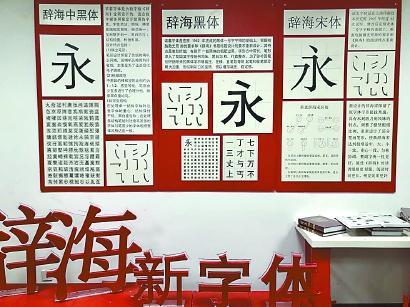
第四代传承人为《辞海》(第七版)设计的新字体。 资料图片
用手机发微信、翻开书本阅读……当一个个汉字如同空气一般出现在你眼前时,你可曾想过,这些字体是由谁设计出来的?
新闸路1209弄60号印研工坊内,“现代汉字印刷字体发源地”和“上海印刷字体展示馆”两块招牌今天同时揭牌。人们最常用的宋体、黑体、仿宋、楷体这四大经典印刷字体,正是在这里诞生的。
弄堂口的门牌已改造一新,显示“印研工坊”始于1956年。新中国成立后在上海建立的专业印刷科研机构——上海市印刷工业公司试验室驻扎在这里,1961年8月改为上海印刷研究所,1965年更名为上海印刷技术研究所。去年,上海印刷集团和上海印刷技术研究所在“印研工坊”园区改建完成,搬回新闸路1209弄60号。
新改建后的“印研工坊”园区处处可见对印刷文化、字体文化的展示。面向市民开放的“上海印刷字体展示馆”分“字体馆”与“非遗馆”,在此可一览汉字印刷体的源流与发展。
现代汉字印刷字体两个“源头”
何以能称“现代汉字印刷字体发源地”?新闸路的这处小楼里,找得到两个“源头”。
其一是新中国的印刷字体源头。在相当长一段时期,我国汉字字体、字形杂乱,异体、变体混合使用,严重影响印刷质量和阅读效果,更导致我国参加国际书籍装帧博览评比无功而返。1959年,文化部召开会议指导上海率先进行“印刷字体改革”,以印研所为基地,集聚了沪上美术创意有功力、书写正楷有造诣、雕刻字模有经验的三股人才,成立50多人组成的字体研究室。于是,字体设计师这一职业,从1960年开始在中国创立。
印研所字体研究室的设计人员耗时5年,相继完成宋、黑、楷、仿四种常用印刷字体的创写设计,总计8万字,分别用于印刷新版横排本《毛泽东选集》《辞海》《汉语大字典》及政经科教图书、期刊杂志和中小学课本,我国出版物和印刷品面貌就此焕然一新。在创作的同时,设计人员还根据标准化、规范化的笔形、字形编制出《印刷通用汉字字形表》,报经国家文字改革委员会审核通过,成为我国印刷汉字模板,为新中国推广简化字和汉字使用的规范化作出重要贡献。
其二是汉字印刷字体的数字化发展始于此。上世纪80年代,上海印刷技术研究所将宋、黑、楷、仿四大品种的专用字稿作为与英国蒙诺公司合资的投资,首次购进国际先进的激光照排设备,后又将这四种字体的原始字稿复印无偿提供国家“748”工程、“汉字信息处理”重大项目。这些字体与现代数字信息技术结合,成为发明“汉字信息处理激光照相排字技术”的原创母体,之后普遍进入海内外汉字字库,派生出千姿百态的后代字体。
2009年,上海印刷技术研究所申报的汉字印刷字体书写技艺被列入上海市第二批非物质文化遗产项目名录。
五道工序反复雕琢出完美字体
在印研所标志性的旋转扶梯,1964年夏日,6个穿衬衫的小伙站在三到四楼的拐角拍照,最前面的陈其瑞21岁,年纪最小,身后张家声、过祖良、陈永海、许柏康、徐学成等拾级而上。如今,旋转扶梯的墙面成为非遗传承人墙,23位非遗传承人的照片拾级而上。排在陈其瑞之前的11位“第一代”传人皆已谢世。
1943年出生的陈其瑞18岁进入印研所,跟着当时所里的前辈们参与“黑一体”创写,上世纪70年代与张家声共同主持“新魏体”开发,至今被广泛使用。“当时,平均一个人每天能写四个字。”陈其瑞介绍。
设计字体要经过五道工艺流程。首先是铅稿,设计者用铅笔在专用字稿纸上勾勒出字稿轮廓,这是字体成败的关键;第二步是画线,用画线工具直线笔(鸭嘴笔)画出黑色线条,要求墨色均匀一致,线条光洁;第三步是勾描,用描笔将设计好的字形轮廓勾描出来;第四步是填黑,将黑墨色填满勾描内的留白部分;最后一步是描白,严格依照字样规范、笔形进行修整、精加工,用白色颜料涂去毛刺、毛边,使线条、笔形光洁优美。在“非遗馆”展示的当年字体设计原稿上,铅笔勾勒与描白依然可见,有的字还有贴补痕迹,可见当年设计师们经过反复雕琢才有了日后应用的完美字体。
1957年出生的汉字印刷字体书写技艺第三代传承人原伟民介绍,40多年前诞生的“宋一体”“黑一体”是新中国第一款专为《辞海》正文和配套标题用字所设计的字体;“宋二体”“黑二体”是专为《毛泽东选集》横排本正文及配套标题设计的首款字体;“仿宋体”主要为党政机关文件正文排版设计;“正楷体”主要为排印小学教科书和少儿读物设计。“常用经典字体的母体,就在上海,就在印研所。希望展示馆的开放能让更多人了解现代汉字印刷字体的起源和发展,了解汉字印刷字体的设计规范和创写工艺,更加热爱汉字。”原伟民说。
上世纪70年代,“书法体”首度引入印刷字体,首先选中的就是当时很受百姓喜欢、适合做店招和刷标语的“新魏体”,并确定找书法家来写字模。为了找到合适的书写者,陈其瑞骑着自行车走街串巷,看路两旁的店招。直到今天,陈其瑞仍然喜欢看店招。尽管很少有人知道字体背后的设计者,但他觉得,在那些字体里可以感受到当年辛勤工作的意义。
设计《辞海》(第七版)专用字体
去年在网上,出现一份叫价1万元的上海印刷技术研究所文书档案,其中包含第一代字体设计师的集体签名。这份上世纪60年代的文件背后是关于“宋七体”的一段往事。当时印研所已完成“宋一”“黑一体”“宋二”“黑二体”及“宋三体”,新设计的字体按序应编“宋四”,因沪语谐音不好听而改名“宋七”,即去年离世的汉字印刷字体书写技艺第一代传承人徐学成设计的“康熙字典体”。2010年,90后设计师厉向晨完成含47037个字的“康熙字典体”,在后来的“汉字热”中,成为传统、古典设计风格的代名词,“宋七”也随之重新进入人们的视野。“最美的宋体是哪一款?”有字体爱好者回答,“宋七”。
在新开放的上海印刷字体展示馆里,市民就能发现神秘“宋七体”的故事。最令人惊喜的或许是印研所今年创写的三种新字体的样张——“徽逸体”“逸文体”“新行楷体”。它们的设计者是印研所的年轻人,汉字印刷字体书写技艺的第四代传承人。这其中,1987年出生的万世琴去年获得“上海工匠”称号,代表作包括填补相关领域空白的“古琴减字谱楷体”。
刚刚面世的《辞海》(第七版)所使用的三套专用字体就是万世琴与团队设计完成的。其中“辞海黑体”在“黑一体”基础上重新设计,笔形纤细,字体方中带长,笔形渗入我国汉字传统书写味。“辞海宋体”在经过42次试写、修改后定形的“宋二”基础上设计,笔形更柔和、厚实,长时间阅读更舒适。“辞海中黑体”是为数字版《辞海》全新设计的,适合数字屏幕显示,字体简洁、明快。(记者 施晨露)